Diseñar un logotipo que se quede grabado en la memoria es fundamental para construir una identidad de marca sólida, y uno de los elementos clave para lograrlo es la tipografía.
Escoger la fuente adecuada puede transformar por completo tu logo: hacerlo más reconocible, transmitir los valores correctos y reforzar la personalidad de tu marca.
En este artículo te mostramos una selección de 40 tipografías que funcionan muy bien en logotipos, además de algunos consejos prácticos para ayudarte a elegir la que mejor encaja con tu proyecto. Ya estés buscando una fuente clásica, moderna o con un toque más artístico, aquí encontrarás un montón de ideas para inspirarte.
Los 4 tipos principales de familias tipográficas empleadas para el diseño de logotipos
A la hora de diseñar un logotipo, existen cuatro grandes familias tipográficas que conviene conocer: serif, sans serif, script y display. Cada una tiene características propias y transmite emociones o ideas distintas.
A continuación, te contamos en qué consiste cada una de ellas y te proponemos diez ejemplos populares dentro de cada categoría.
Tipografías serif para logotipos
Las fuentes serif son clásicas y elegantes. Se reconocen fácilmente por los pequeños remates o líneas que se encuentran al final de los trazos de cada letra. Este estilo suele asociarse con la tradición, la confianza y la autoridad. Aquí van diez ejemplos que funcionan especialmente bien en logotipos:
- Times New Roman: Todo un clásico. Famosa por su gran legibilidad y apariencia formal, fue diseñada originalmente para su uso en periódicos. Hoy es habitual en entornos académicos y profesionales. Sus líneas limpias y proporciones equilibradas la convierten en una apuesta segura tanto para textos largos como para titulares.
- Georgia: Una fuente serif moderna y perfecta para pantallas. Su diseño, con una altura de x mayor y formas abiertas, facilita mucho la lectura digital. Tiene una estética atemporal que resulta ideal para páginas web o textos extensos.
- Garamond: Elegante y sofisticada, Garamond es una fuente con mucha historia que se asocia a menudo con marcas de lujo. Sus remates delicados y curvas suaves aportan un aire distinguido, ideal para libros, invitaciones o materiales de papelería con un toque premium.
- Baskerville: Una tipografía que equilibra lo tradicional con lo contemporáneo. Con un marcado contraste entre trazos gruesos y finos, ofrece un acabado elegante y profesional. Muy utilizada en diseño editorial y branding con inspiración clásica.
- Palatino: Fuente versátil que funciona muy bien tanto en impresión como en pantalla. Sus formas amplias y su espaciado generoso mejoran la legibilidad, mientras que su diseño transmite calidez y sofisticación.
- Caslon: Una de las tipografías más emblemáticas de la historia editorial. Con un diseño robusto y fiable, es perfecta para libros, revistas o cualquier soporte donde se quiera transmitir autoridad y tradición.
- Century Schoolbook: Fuente sencilla y clara, muy conocida por su alta legibilidad. Suele utilizarse en materiales educativos, libros para niños o publicaciones formativas. Sus formas redondeadas la hacen accesible y fácil de leer.
- Bookman: Tipografía serif con gran presencia visual. Su trazo grueso y sus formas anchas captan rápidamente la atención, por lo que es ideal para titulares, carteles o diseños que buscan impacto sin renunciar a la elegancia.
- Minion: Clásica y cercana, Minion tiene un estilo cálido que encaja tanto en proyectos impresos como digitales. Sus proporciones equilibradas y detalles refinados la han convertido en una de las favoritas entre diseñadores profesionales.
- Sabon: Si lo que buscas es transmitir sofisticación, Sabon es una gran elección. Sus formas refinadas y su estructura coherente la hacen perfecta para materiales impresos de alta gama como catálogos, invitaciones o papelería de marca.
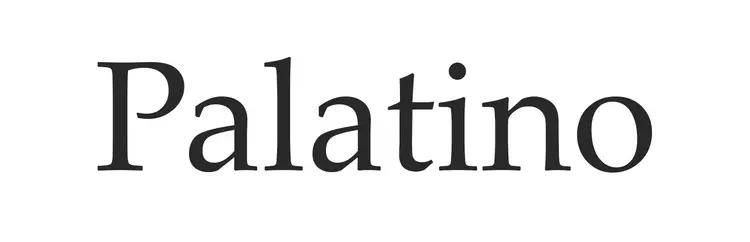
Tipografías sans serif para logotipos
Las fuentes sans serif tienen un estilo moderno, limpio y funcional. Se caracterizan por la ausencia de los pequeños remates que sí están presentes en las tipografías serif. Transmiten simplicidad, claridad y profesionalidad, por lo que son muy populares entre marcas tecnológicas y empresas con una identidad visual contemporánea.
A continuación, te mostramos diez de las mejores tipografías sans serif para utilizar en logotipos:
- Helvetica es una de las tipografías sans serif más icónicas y atemporales. Famosa por sus líneas limpias, su neutralidad y su enorme versatilidad, fue diseñada en los años 50 y se ha convertido en una de las fuentes más utilizadas del mundo. Gracias a su diseño equilibrado y directo, es ideal para marcas, señalética y comunicación corporativa.
- Arial es una tipografía sans serif ampliamente extendida, conocida por su sencillez y gran legibilidad, tanto en formatos digitales como impresos. Diseñada como una alternativa más actual a Helvetica, presenta curvas algo más suaves y una estructura más abierta. Su uso generalizado en múltiples plataformas garantiza una lectura clara y coherencia visual en cualquier aplicación.
Cómo elegir las mejores fuentes para la creación de logotipos
Elegir la fuente adecuada es un paso fundamental para construir una identidad visual sólida que conecte con tu público. Ya sea que estés arrancando un nuevo proyecto o rediseñando tu marca, la tipografía adecuada puede marcar la diferencia.